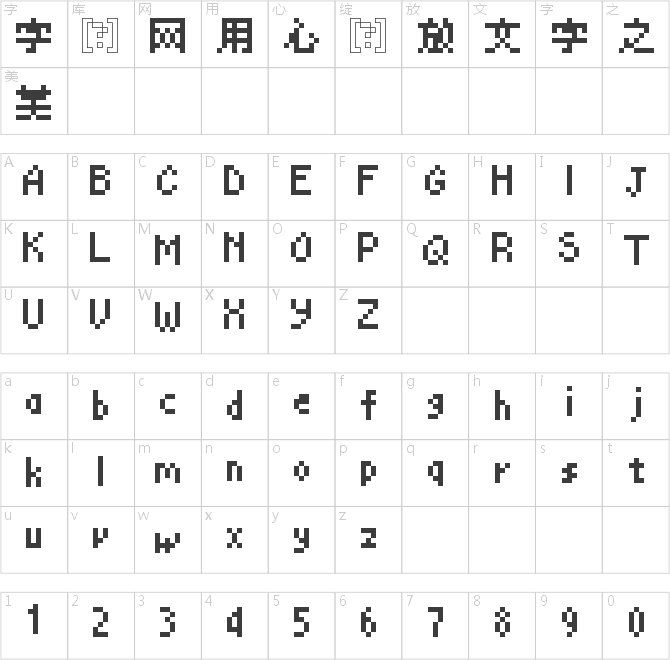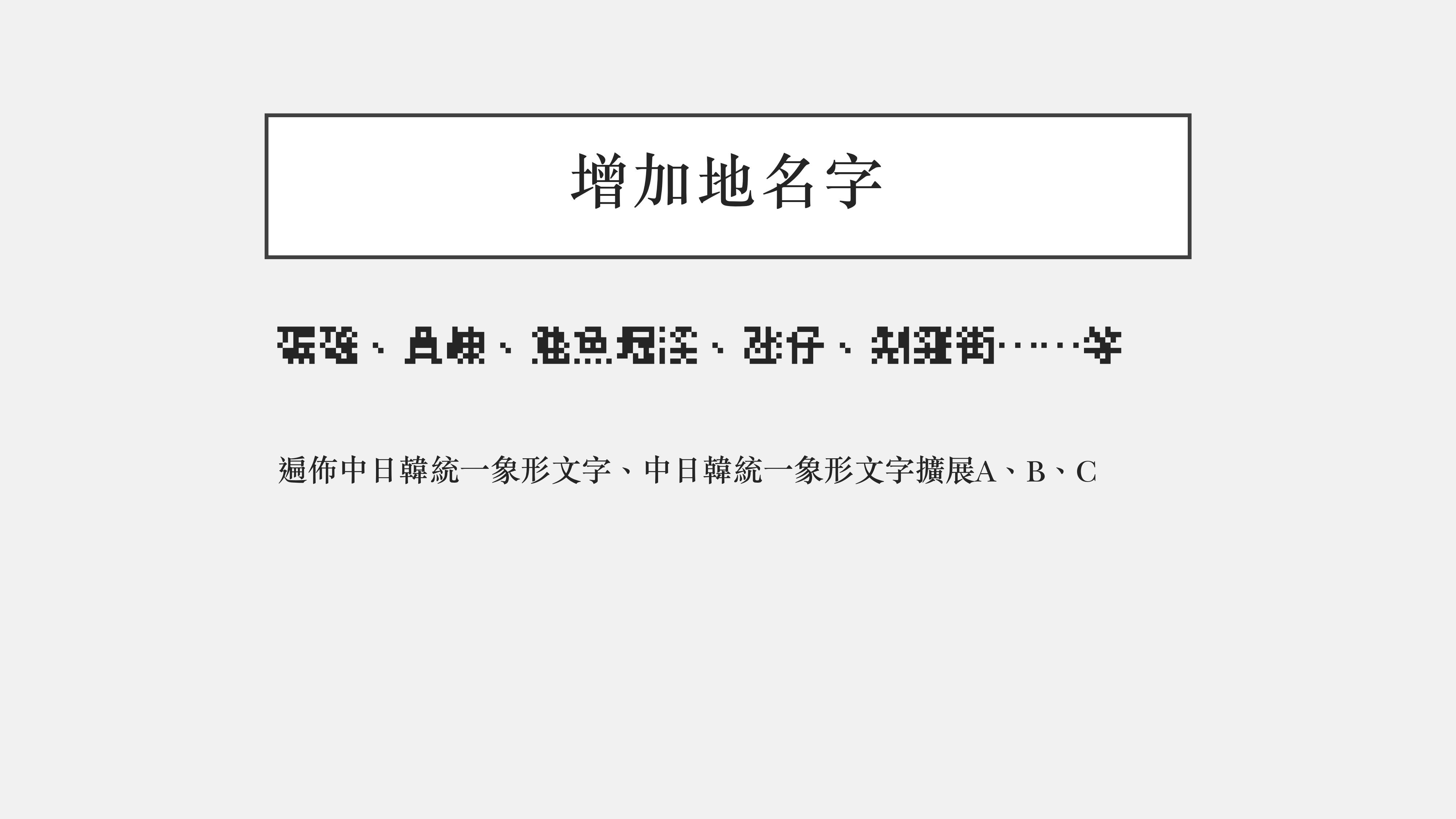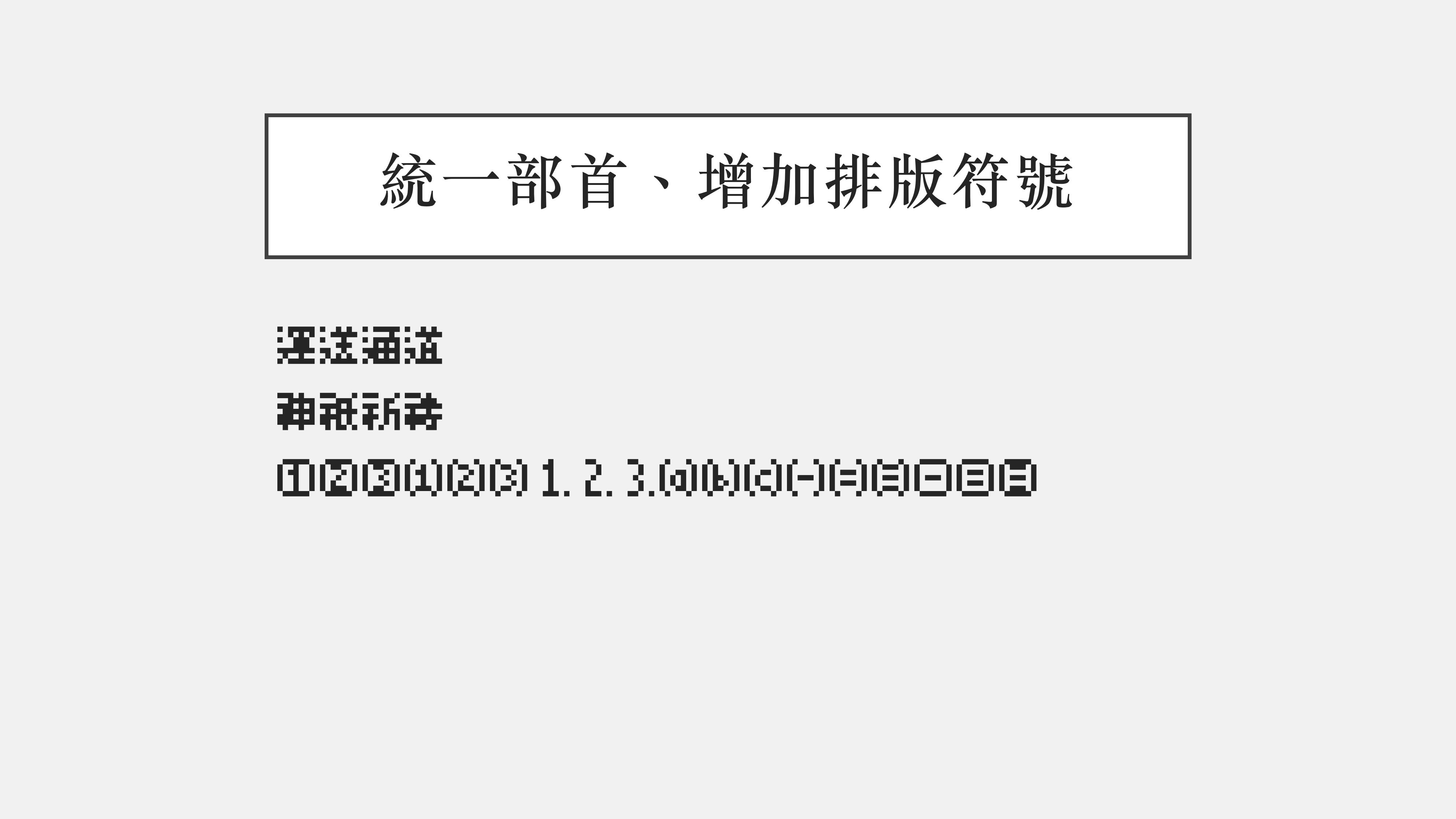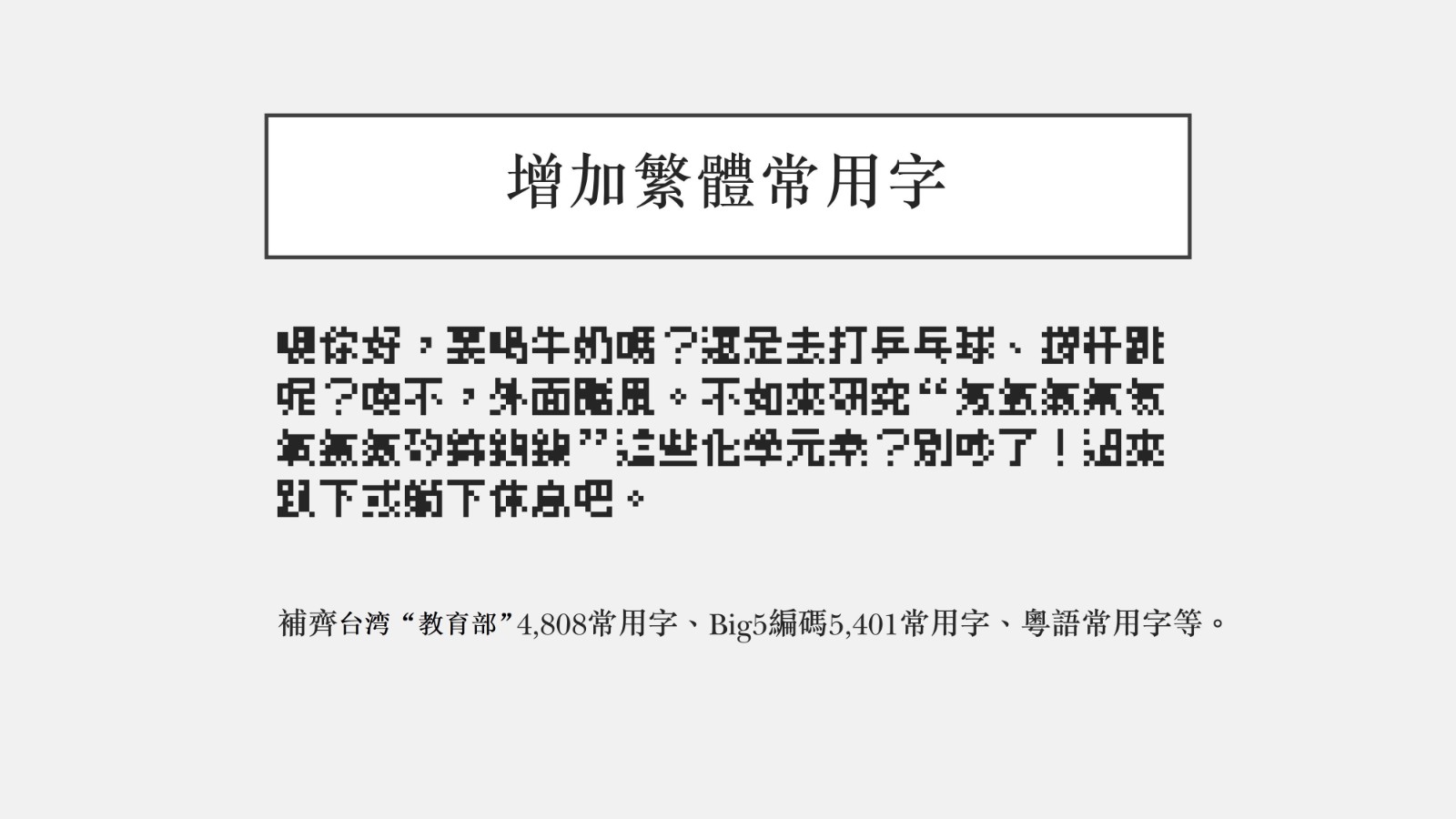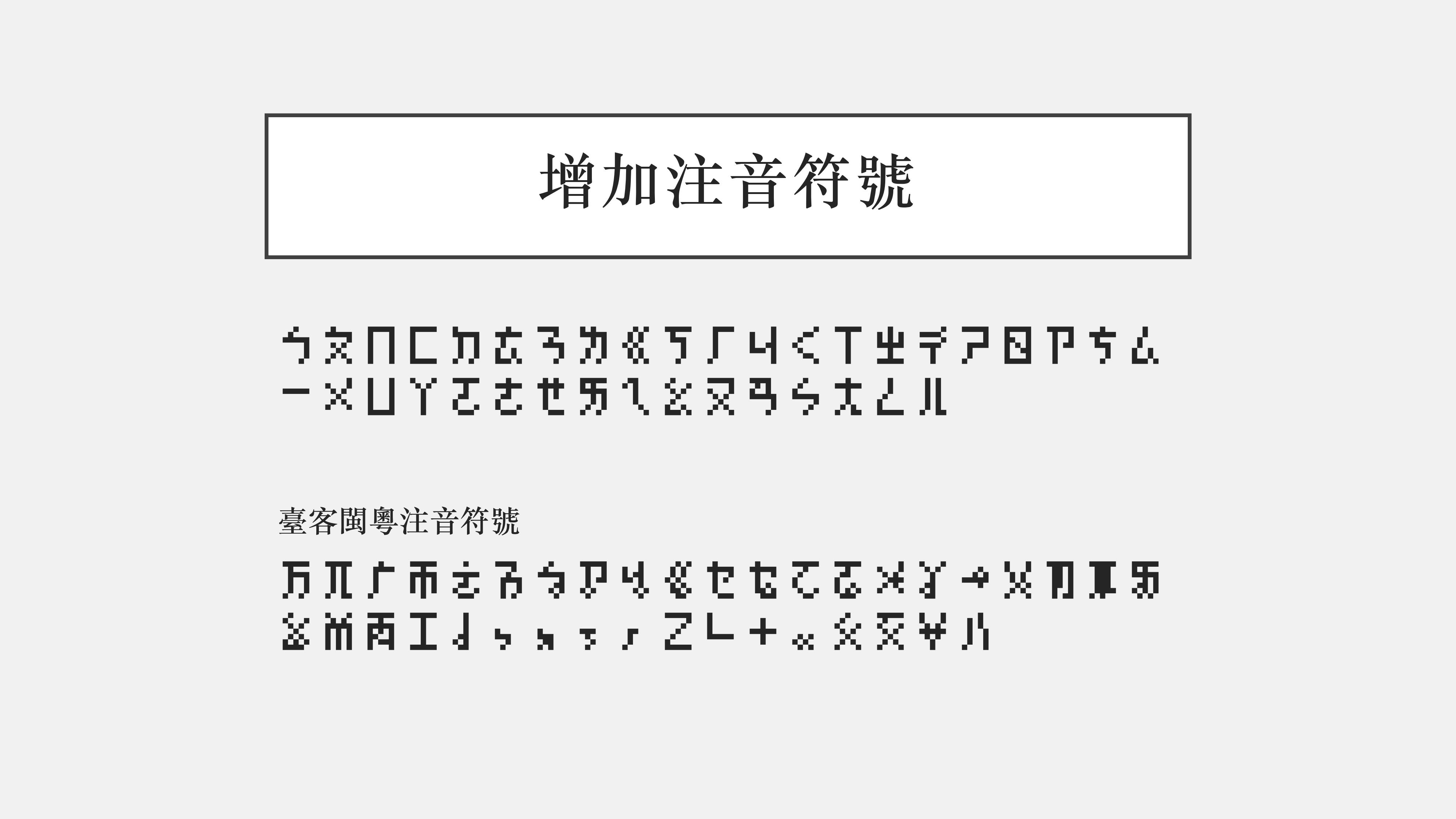
精品點陣體7×7繁體
《精品點陣體7×7 (BoutiqueBitmap7x7) 》是一款基於美咲フォント改作的字型,目的為適合在繁體中文環境中使用。我們改正了一些標點符號、日本習慣寫法、增加近1,000個字符及500個粵語字,使字型使用更方便!
這是一款帶有極強烈的點陣風格的字型,非常適合用在像素畫、遊戲相關主題等等。
?2020/9/2更新版本1.3:增加臺客語漢字、蘇州碼